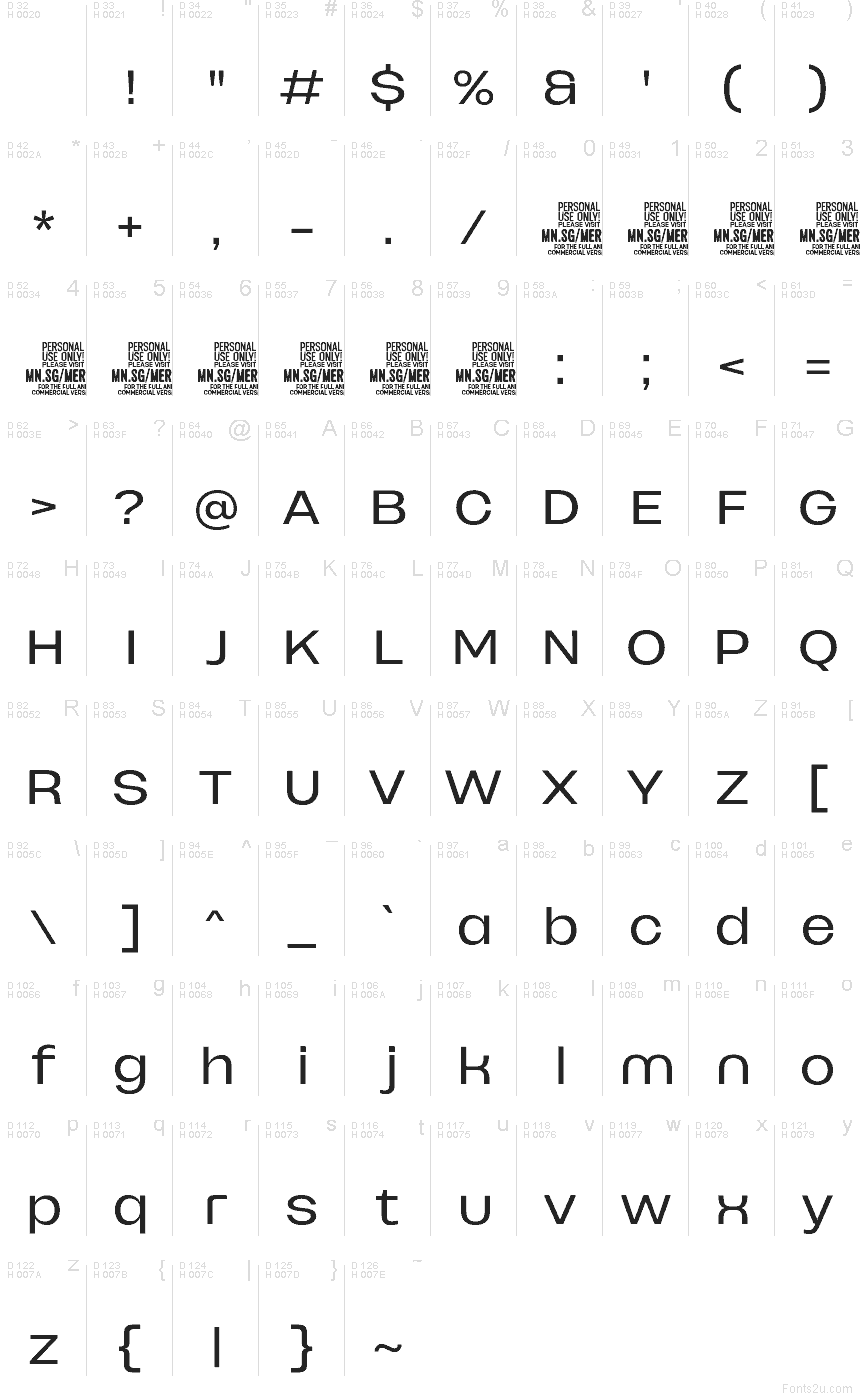
Merica Futurist PERSONAL USE Light
Merica Futurist von Mans Greback ist eine kostenlose, futuristische serifenlose Schrift mit einer klaren, fast monolinearen Ästhetik und einer prägnanten, geometrischen Rhythmik. Das abgerundete „e“, das offene Schriftbild und die präzise beschnittenen Kurven verleihen den Buchstaben eine elegante Sci-Fi-Ruhe, die eher stromlinienförmig als mechanisch wirkt.
Diese kostenlose Schriftart eignet sich hervorragend für das Branding von Technologieprodukten, Musik-Covern, Interface-Titeln, Plakat-Überschriften und Magazin-Titelzeilen, bei denen ein moderner Look gefragt ist, ohne dabei zu industriell zu wirken. Sie ist zudem ideal für kurze Titel und Wortmarken geeignet, da die weichen Kurven und reduzierten Formen selbst in kompakten Formaten für ein frisches, zeitgemäßes Erscheinungsbild sorgen.